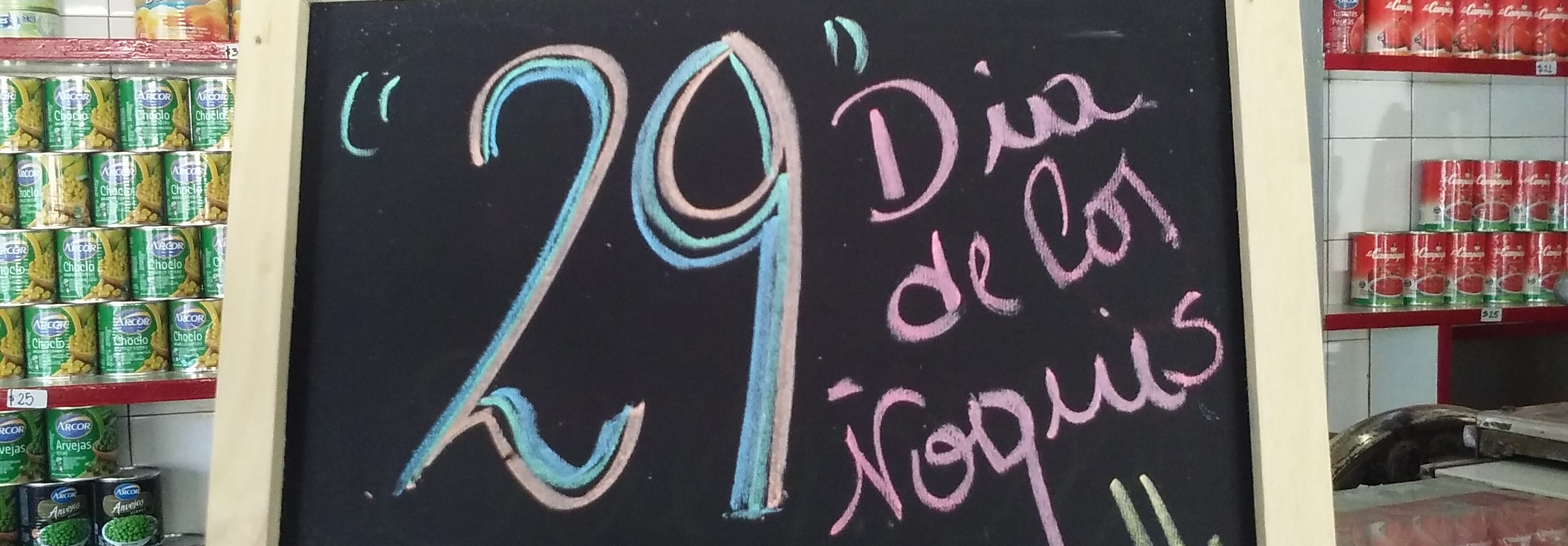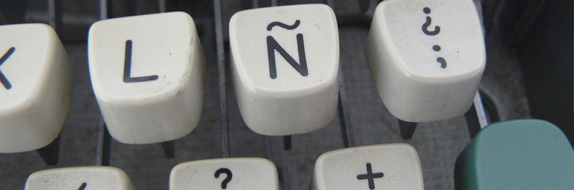
La eñe también es gente, por María Elena Walsh
La culpa es de los gnomos que nunca quisieron ser ñomos. Culpa tienen la nieve, la niebla, los nietos, los atenienses, el unicornio. Todos evasores de la eñe. ¡Señoras, señores, compañeros, amados niños! ¡No nos dejemos arrebatar la eñe! Ya nos han birlado los signos de apertura de interrogación y admiración. Ya nos redujeron hasta la apócope. Ya nos han traducido el pochoclo. Y como éramos pocos, la abuelita informática ha parido un monstruoso # en lugar de la eñe con su gracioso peluquín, el ~. ¿Quieren decirme qué haremos con nuestros sueños? ¿Entre la fauna en peligro de extinción figuran los ñandúes y los ñacurutuces? ¿En los pagos de Añatuya cómo cantarán Añoranzas? ¿A qué pobre barrigón fajaremos al ñudo? ¿Qué será del Año Nuevo, el tiempo de ñaupa, aquel tapado de armiño y la ñata contra el vidrio? ¿Y cómo graficaremos la más dulce consonante de la lengua guaraní? "La ortografía también es gente", escribió Fernando Pessoa. Y, como la gente, sufre variadas discriminaciones. Hay signos y signos, unos blancos, altos y de ojos azules, como la W o la K. Otros, pobres morochos de Hispanoamérica, como la letrita segunda, la eñe, jamás considerada por los monóculos británicos, que está en peligro de pasar al bando de los desocupados después de rendir tantos servicios y no ser precisamente una letra ñoqui. A barrerla, a borrarla, a sustituirla, dicen los perezosos manipuladores de las maquinitas, sólo porque la ñ da un poco de trabajo. Pereza ideológica, hubiéramos dicho en la década del setenta. Una letra española es un defecto más de los hispanos, esa raza impura formateada y escaneada también por pereza y comodidad. Nada de hondureños, salvadoreños, caribeños, panameños. ¡Impronunciables nativos! Sigamos siendo dueños de algo que nos pertenece, esa letra con caperuza, algo muy pequeño, pero menos ñoño de lo que parece. Algo importante, algo gente, algo alma y lengua, algo no descartable, algo propio y compartido porque así nos canta. No faltará quien ofrezca soluciones absurdas: escribir con nuestro inolvidable César Bruto, compinche del maestro Oski. Ninios, suenios, otonio. Fantasía inexplicable que ya fue y preferimos no reanudar, salvo que la Madre Patria retroceda y vuelva a llamarse Hispania. La supervivencia de esta letra nos atañe, sin distinción de sexos, credos ni programas de software. Luchemos para no añadir más leña a la hoguera dónde se debate nuestro discriminado signo.
Letra es sinónimo de carácter. ¡Avisémoslo al mundo entero por Internet! La eñe también es gente.